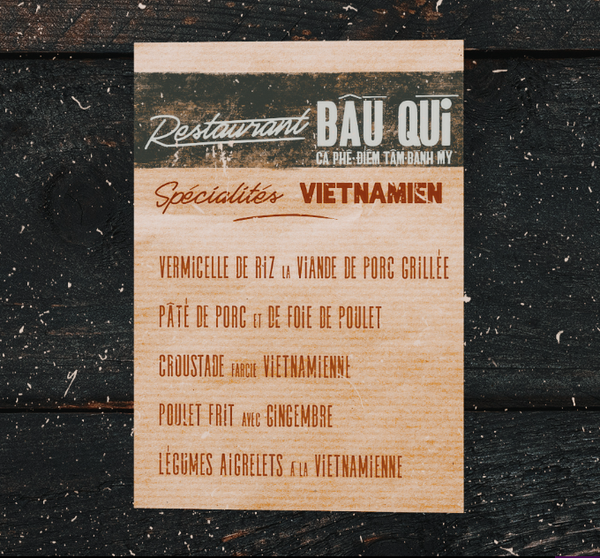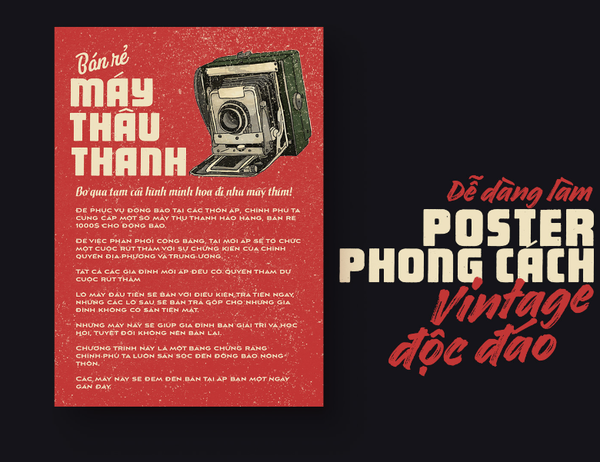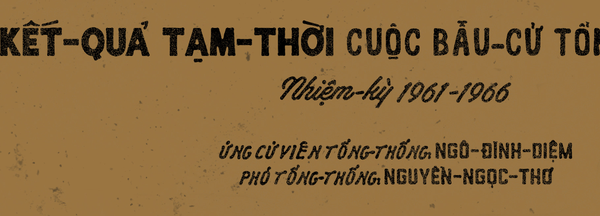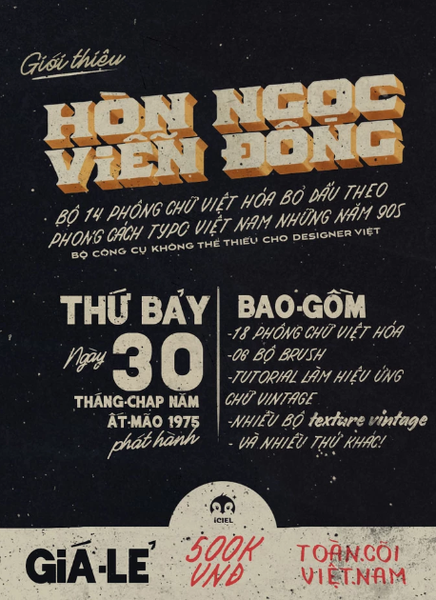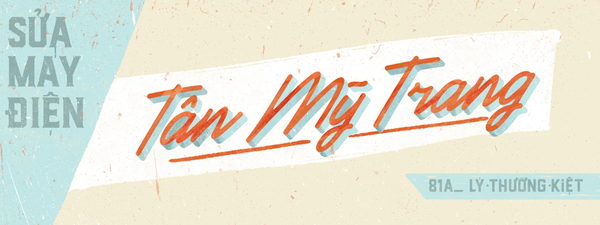
Download font Hòn Ngọc Viễn Đông của iCiel mang cung cách các bảng hiệu - biển bảng nước việt nam thập niên 90 mang hơi hướng cổ điển. Bộ font này phát huy thành quả đã đạt được từ bộ font trị giá xưa cũ của iCiel, đương nhiên cả 2 bộ font này đều có phí. Font chữ HonNgocVienDong phong cách xưa cũ, dựa theo ý nghĩ gợi lên về các bảng hiệu Sài Gòn xưa , logo từ thế kỷ 19, thời khắc mà tp Hồ Chí Minh còn được ví von là Hòn Ngọc Viễn Đông của châu Á.
Đôi nét về bộ font Hòn Ngọc Viễn Đông của iCiel
Thật sự thì, xu hướng thể hiện lại phông chữ thời trước tại đất nước chúng ta đã ra đời trên mạng xã hội facebook cách đây không lâu. Tuy nhiên để biến những ý nghĩ đó trở thành kết quả thực tiễn để một vài người khả dụng thì chẳng phải người nào cũng thực hiện được, đặc biệt là với những người không chuyên về thiết kế font chữ.
Bộ font Hòn Ngọc Viễn Đông việt hóa do bạn Nguyễn Hồng Nhung, chủ của hãng iCiel, thiết kế bằng những cung cách bảng hiệu nước ta những năm 90. Nắm tâm thế của đông đảo mọi người dùng Việt thích dùng cái gì đó đậm chất bản sắc đồng bào và mang hơi hướng trở lại thời kì xưa cũ, bởi đó mà iCiel đã giới thiệu bộ phông mới có tên Hòn Ngọc Viễn Đông.
Tác giả đã mất tới hai tháng mày mò tìm hiểu để mai mối bộ font #honngocviendong mang đựng phong cách Sài Gòn thửa trước , với 18 phông chữ được việt hóa theo cung cách vintage. Đây chính là bộ font độc quyền không có nơi nào sở hữu. Tác giả phải tìm hiểu rất nhiều hình ảnh bảng hiệu Sài Gòn, rồi điều chỉnh, thiết kế sao cho bắt mắt nhất , tuy nhiên không mất đi cái hồn của font chữ xưa.
Tác giả bộ font Hòn Ngọc Viễn Đông – iCiel là ai ?
ICiel là kí hiệu của impérissable ciel , nhãn hàng do một bạn nữ tại thủ đô tên Nguyễn Hồng Nhung tạo nên để tiến triển các phông chữ tiếng việt , hầu hết là việt hóa rồi cung cấp cho dân designer. Trên website của iCiel, phần cho ra mắt nêu rõ :
“Mình là một bạn nữ có năm sinh là 1992 sống tại thủ đô, có say mê với nghệ thuật, nét thẩm mỹ và nổi bật là ký tự. Hiện giờ công tác chính của bản thân là việt hoá font cho những công ty, đối tượng trong ngành xây dựng. Dã từng cộng tác với một số doanh nghiệp lớn như : Richard Moore Associates, Leo Burnett Vietnam, Canifa, Samsung, Alpha Books, Soyon, Redder ...
Giữa năm 2016 mình mở đầu cộng tác với google để việt hoá font cho họ. Mình đã được đến trụ sở Google ở New York, Mỹ để tập sự và xây dựng lộ trình tạo nên tuyển tập Google fonts. Tại thời điểm này mình đã hiểu được không ít chuyện từ Google và kỹ thuật làm font hot của họ. Bây giờ mình đã về nước và sẽ tiếp tục công việc việt hoá font.”